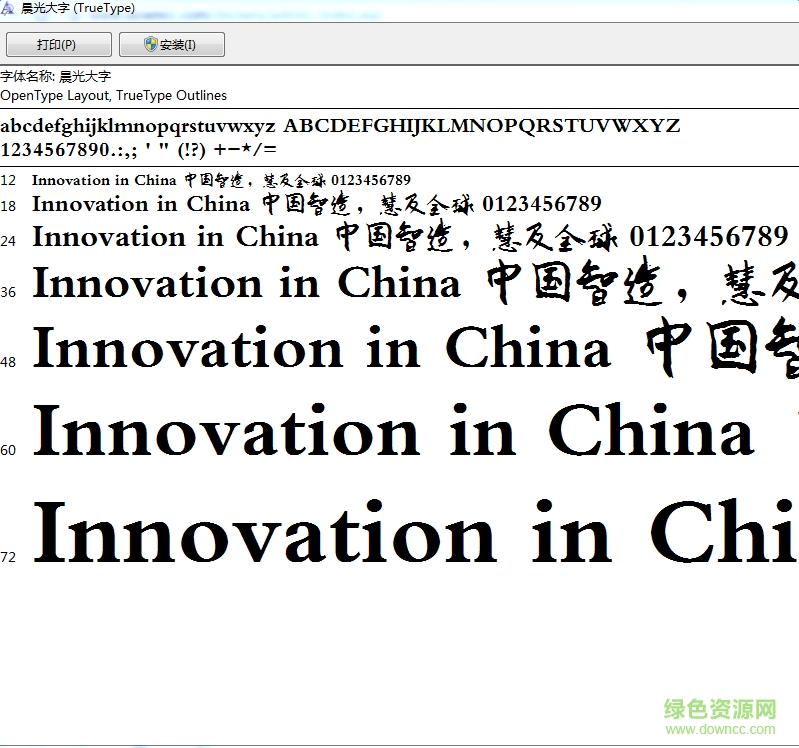
晨光大字簡(jiǎn)體是一款晨光類創(chuàng)意霸氣風(fēng)格字體軟件,晨光大字體筆畫隨意卻不失整體的工整性,粗細(xì)相間,非常的時(shí)尚,還有更多類似好看字體歡迎來綠色資源網(wǎng)下載體驗(yàn)!
晨光大字簡(jiǎn)體是一款應(yīng)用于藝術(shù)設(shè)計(jì)方面的簡(jiǎn)體中文字體,該字體筆畫粗壯,尾部的甩尾有力且有豐富的筆觸細(xì)節(jié),大字效果突出且引人注目;并且最大程度還原作者書寫字形,細(xì)節(jié)表現(xiàn)完整,且字庫(kù)完整,可以廣泛應(yīng)用于名片設(shè)計(jì)、新聞媒體、宣傳海報(bào)、ppt、影視制作以及內(nèi)容用字等領(lǐng)域。
該字體粗獷有力,盡顯手寫體灑脫氣息,整體效果十分酷炫好看,盡顯書法大師的魅力,用來??嵩俸线m不過了!